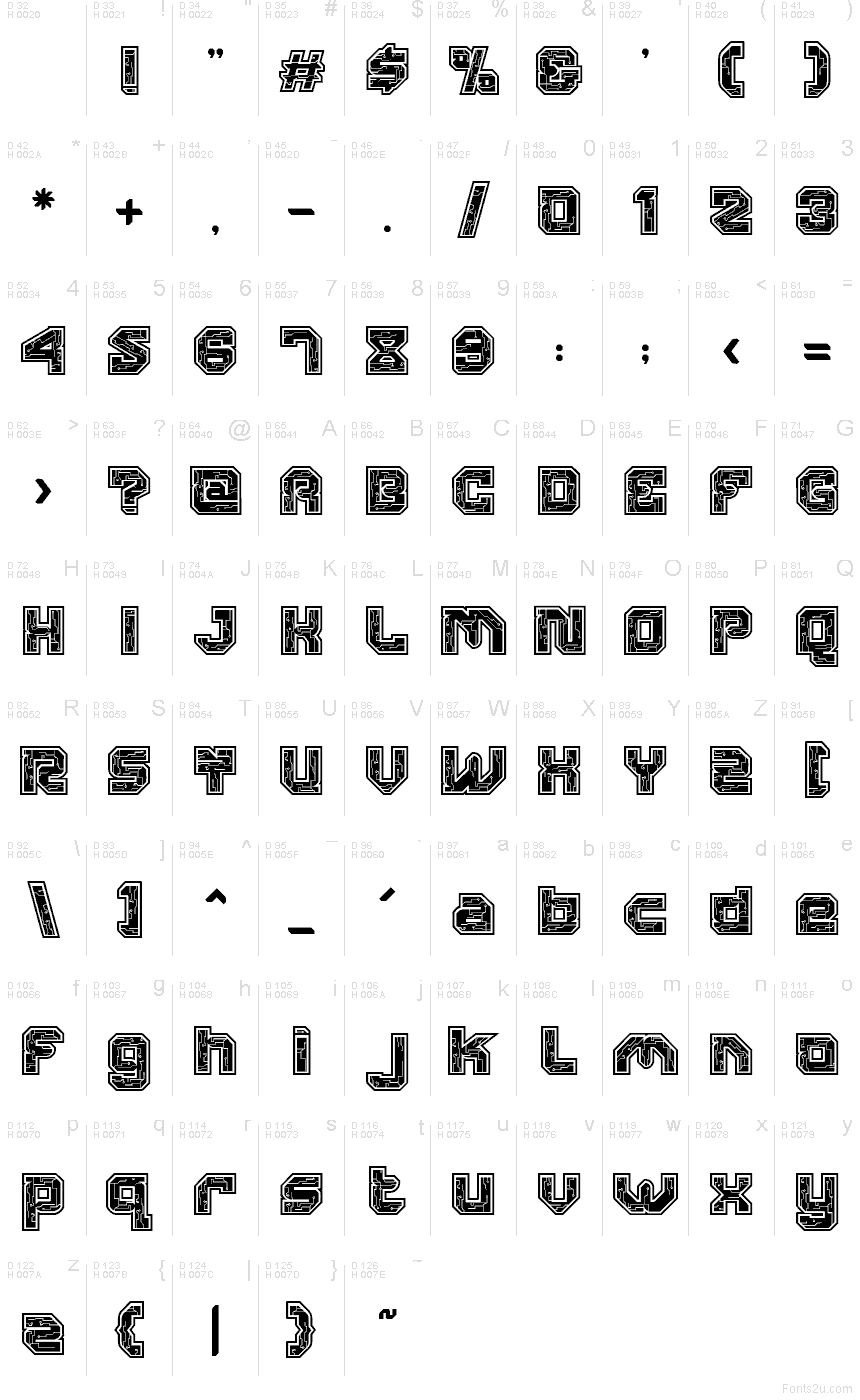
Cyber Crown Two od Putracetol Studio je bezplatné futuristické písmo typu display, vytvořené podle vzoru cest na deskách plošných spojů se zkosenými okraji. Opakující se tahy, tečky připomínající uzly a hranaté rohy dodávají písmenům vzhled, jako by byla vyryta do technického panelu, spíše než aby šlo o pouhé narušení povrchu.
Tato grafická struktura dodává krátkým nadpisům jasný účel v herních overlayích, e-sportovním brandingu, sci-fi plakátech, bannerech pro streamery i technických eventových grafikách. Písmo skvěle poslouží i na obalech nebo sociálních sítích, kde je potřeba digitální, technická textura, protože vnitřní linky písmo oživují, i když jsou celkové tvary blokové a kompaktní.